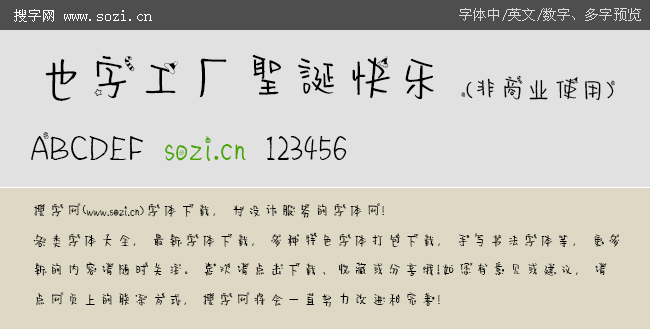
也字工廠圣誕快樂
搜字網給大家提供一款也字工廠圣誕快樂(非商業使用)中文字體下載,也字工廠圣誕快樂是一款略帶卡通風格的手寫字體,字形可愛,又帶有卡通圖案裝飾,非常有趣味性。適合應用于兒童繪本、兒童海報、網頁設計等應用(此字體為個人非商用版,商用可以聯系:官方網址:https://yefont.com/home,聯系方式:13798980448)。